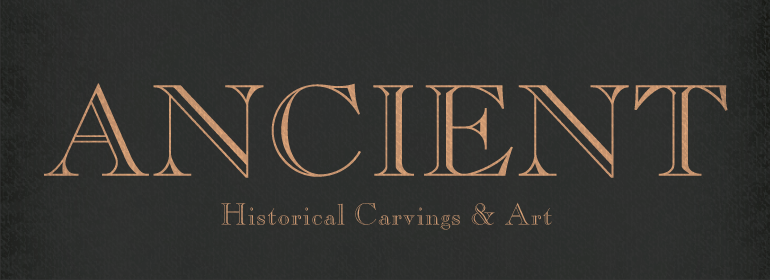
Caslon™ Open Face
在20世纪40年代,开放的、外轮廓或者内轮廓风格的字体变得流行起来。去掉常用的字重便获得了一个清晰的字形。在Caslon Open Face中,右侧笔触被加重了,略微带有三维效果。Caslon Open Face的上伸部很大,该版本的整体设计与Caslon 3 Roman无关。这款Caslon Open Face字体非常适合用于个人文具,也可以用于寻求装饰性但效果出众的句子。
Open, outline or inline faces became very popular in the 1940's. By removing the usual weight, a clear-cut letterform is achieved. In Caslon Open Face, the right-hand strokes are accentuated, providing a slightly three-dimensional effect. The ascenders of Caslon Open Face are large and the overall design of this version does not relate to Caslon 3 Roman. This Caslon Open Face font is good for personal stationery, or sentences where a decorative but distinguished result is sought.